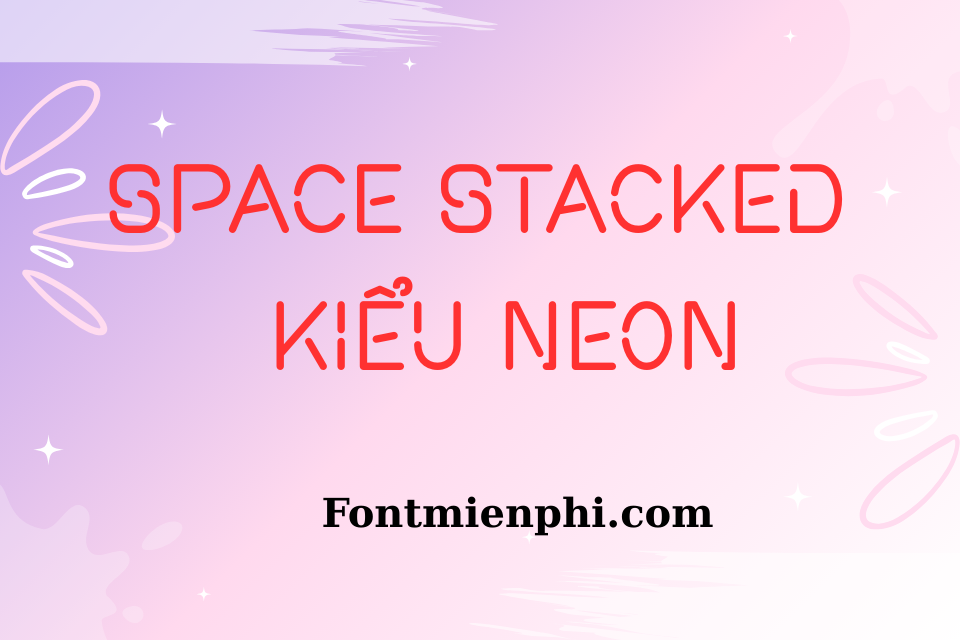
Font Việt hóa 1FTV VIP Space Stacked – Kiểu Neon
Font Việt hóa 1FTV VIP Space Stacked – Kiểu Neon là một kiểu font chữ đặc biệt, mang phong cách hiện đại và sáng tạo. Dưới đây là mô tả chi tiết về font này:
Tính năng nổi bật:
• Phong cách neon: Font chữ này có thiết kế ánh sáng giống như đèn neon, tạo hiệu ứng rực rỡ, thu hút ánh nhìn.
• Chữ cái xếp chồng: Kiểu chữ xếp chồng giúp tạo chiều sâu và sự độc đáo cho từng ký tự, phù hợp với các thiết kế cần sự nổi bật.
• Hỗ trợ tiếng Việt: Font được Việt hóa đầy đủ, bao gồm các ký tự đặc trưng của tiếng Việt như dấu sắc, huyền, hỏi, ngã và nặng.
Ứng dụng:
• Quảng cáo: Rất phù hợp cho biển hiệu, bảng quảng cáo và các sản phẩm cần gây ấn tượng mạnh.
• Thiết kế đồ họa: Dùng trong các tác phẩm nghệ thuật số, poster, bìa sách hoặc album nhạc.
• Truyền thông xã hội: Thích hợp cho các bài đăng trên mạng xã hội nhằm thu hút người xem.
Đặc điểm kỹ thuật:
Font 1FTV VIP Space Stacked – Kiểu Neon không chỉ là một công cụ tạo chữ mà còn là một phần không thể thiếu trong việc tạo ra những sản phẩm thiết kế ấn tượng và sáng tạo.